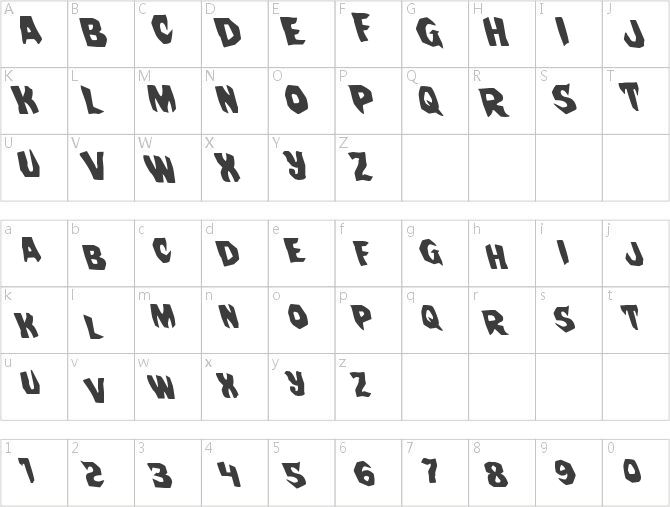
Nightchilde Leftalic 詳情頁
字體名稱: Nightch
Nightchilde Leftalic
Nightchilde Leftalic字體字庫是一款讓人賞心悅目、百看不厭的英文字體,適合各類廣告和產品包裝設計應用,字體大小0.05MB,格式為ttf字體,上傳用戶是志誠設計,作者/版權方為未知